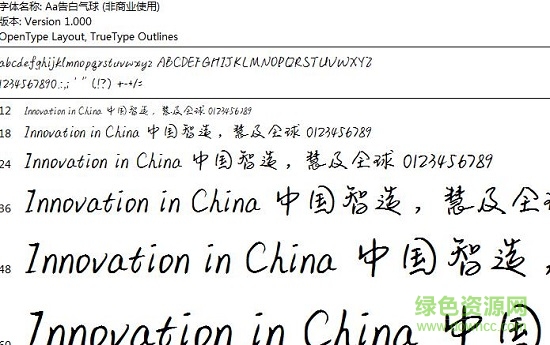
Aa告白氣球體是一款采用手寫風(fēng)格打造的中文字體,字跡灑脫、自由,并且筆畫間的連筆也非常的有特色,有需要使用這款字體的朋友歡迎免費(fèi)下載!
Aa告白氣球體是一款非常好看的手寫字體,這款字體有著鋼筆般書寫的風(fēng)格,并且筆畫流暢自然,每個(gè)字都處理的沉穩(wěn)簡(jiǎn)潔,不僅清晰可辨,還魅力十足!